山东艺术学院设计学院创新创业导师姜海涛作品荣获2018“最美图书奖”“中国自然好书奖”等奖项
2018年度“最美的书”评选11月12日揭晓,来自全国各地20家出版社的25种图书荣膺本年度“最美的书”称号,山东友谊出版社出版的《彩虹汉字丛书(盲文版)·触摸阳光草木》(书籍设计:姜海涛、蔡立国)成功入选,并代表中国参加2019年度“世界最美的书”评选。
“该书通过触摸汉字字形的源流变化,并联系字词背后的文化内涵,帮助盲人顺畅地感知文字,阅读其中内容。书籍封面设计采用黄色与黑色,看上去感觉比较厚重,实际却很轻巧。内页盲文字体触摸感强,并反映出盲文字体的演变过程。同时为适合一般读者阅读特别配以文字与盲文对照,文字也可触摸。本书整体设计简洁明了,视觉效果突出。”
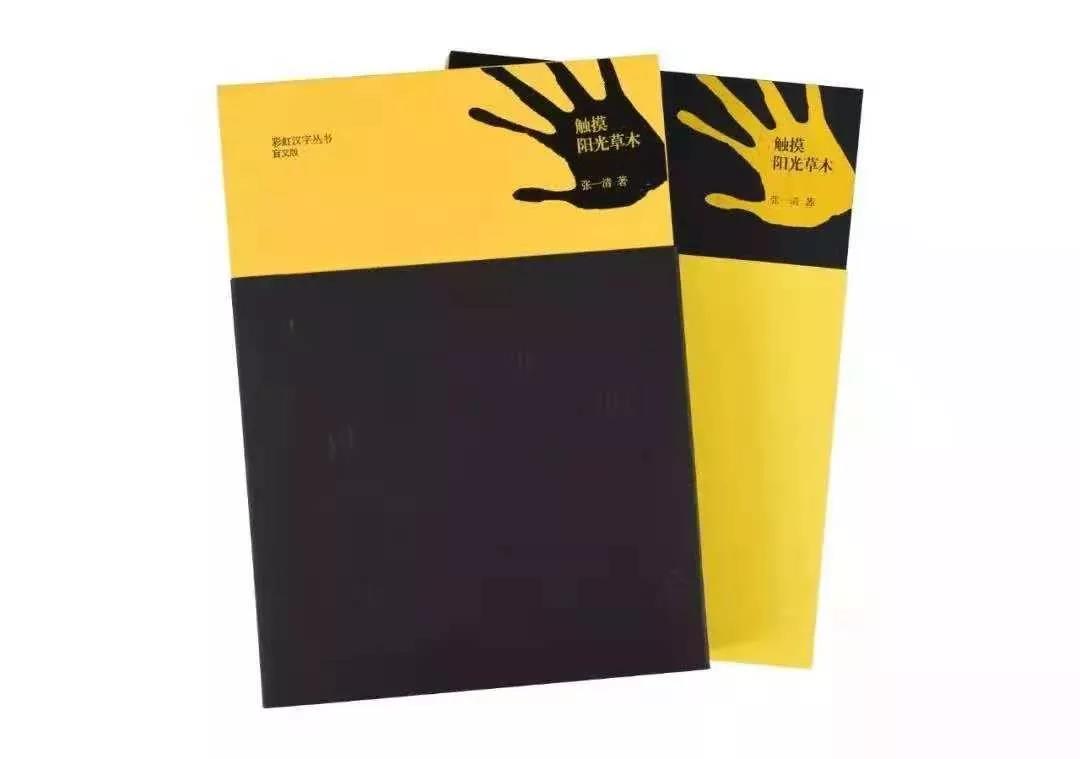
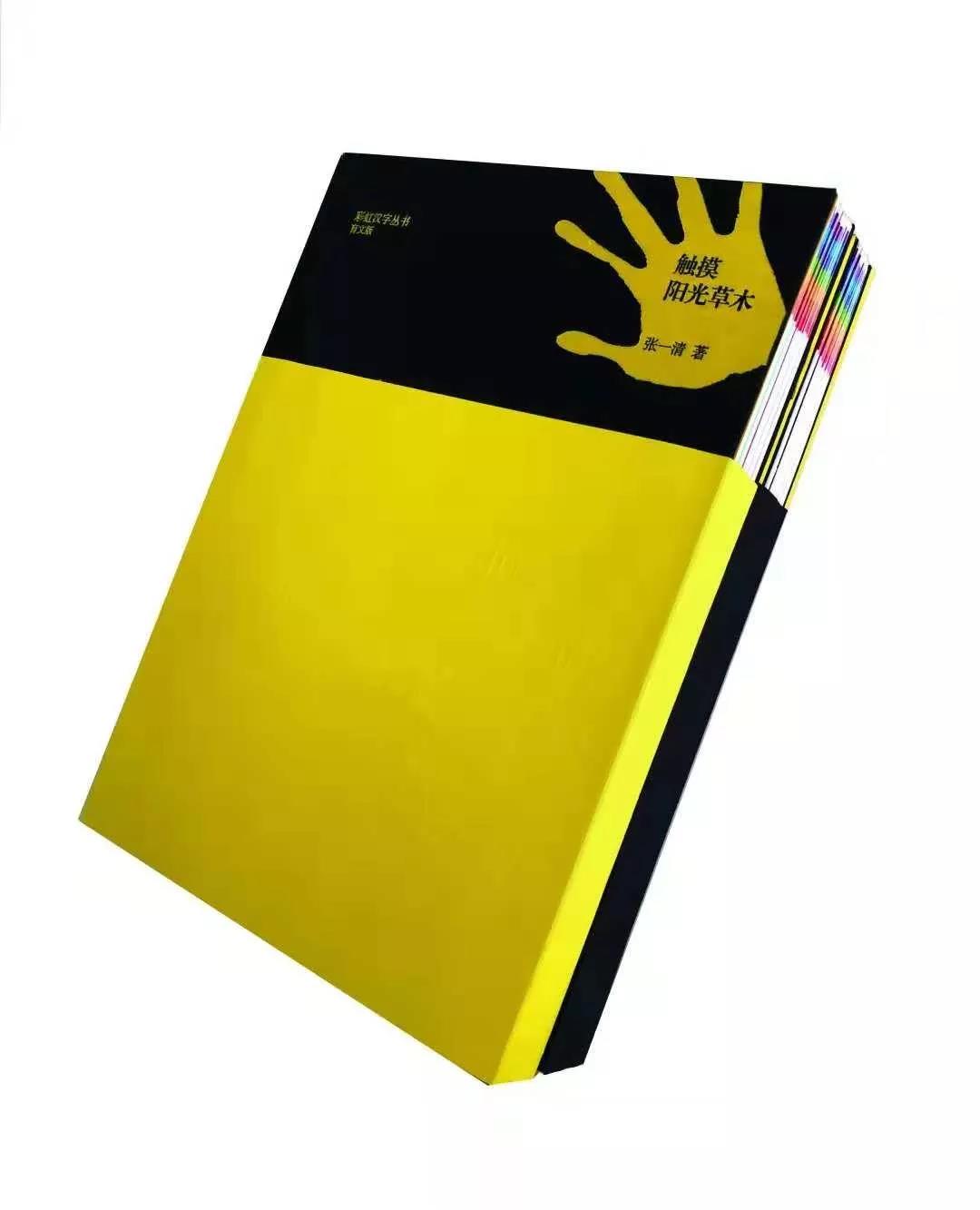
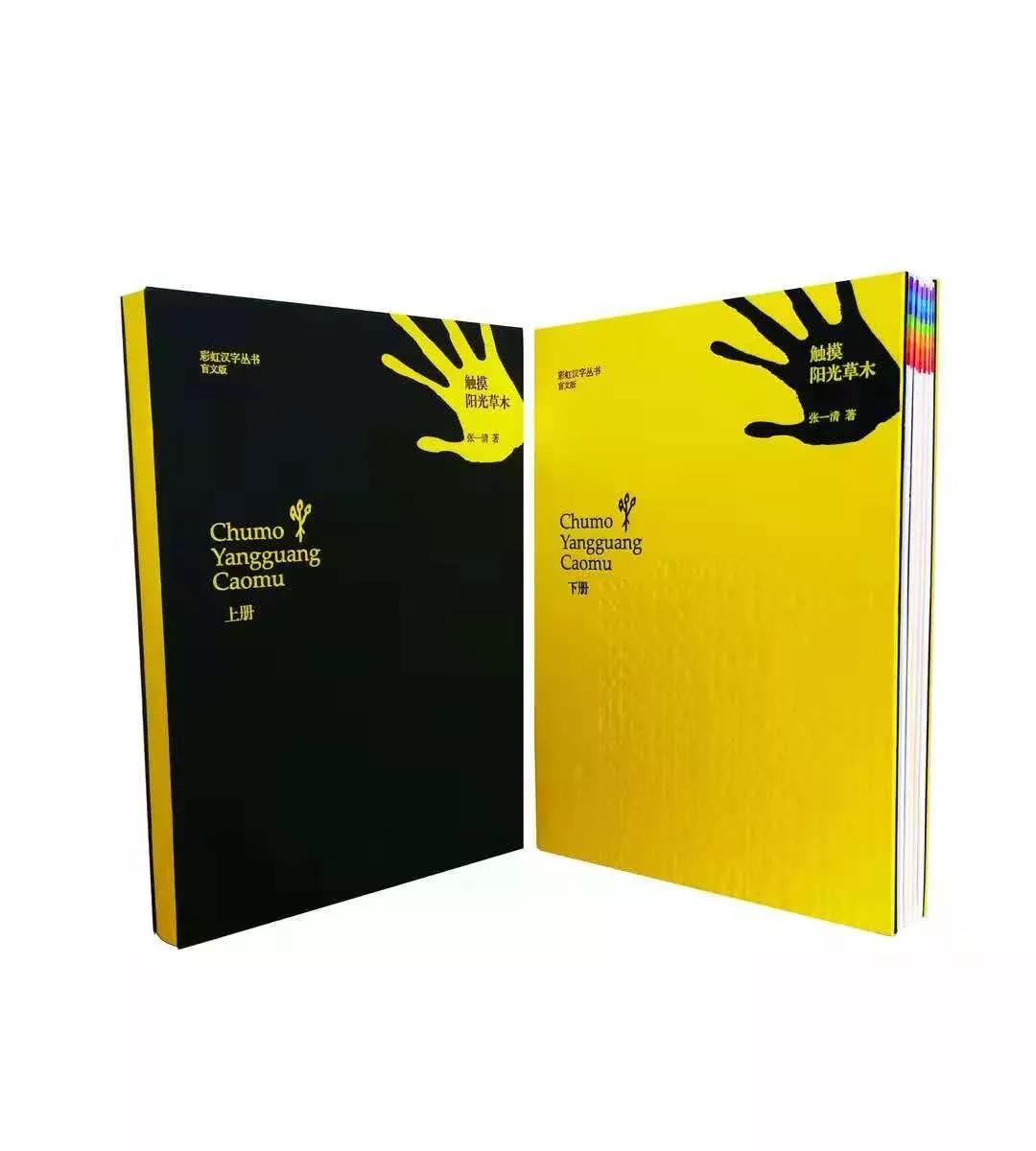
《彩虹汉字丛书(盲文版)·触摸阳光草木》自2017年11月出版以来,以其精美的设计、独特的编辑加工印刷技术、良好的触摸体验、传播传统文化的内容以及对特殊人群的人文关怀,先后获得2017“百道网”年度好书、“2017年度十大数字阅读作品”、“南京最美图书”等奖项,获得2018年度国家出版基金资助。
2018年11月5日晚八点,由阿里巴巴公益基金会主办的首届“中国自然好书奖”颁奖典礼上,该书又入选“年度十大自然好书”,图书责任编辑姜海涛获“年度编辑奖”。《彩虹汉字丛书·触摸阳光草木(盲文版)》这是国内难得一见的专门为盲人群体设计制作的书。
姜海涛在领奖中说,期望这套图书能够给盲人朋友架起一套领略汉字文化之美的彩虹,“大自然最常见的阳光、花草对盲生有自己的感受方式,他们看不到花开,却想触摸花开的声音。我们选取适合盲生理解,又与生活息息相关的汉字解读大自然,使盲点和图形在正文中做到完美结合,克服了以往的盲人图书触感不足和寿命过短的问题,最终实现可触摸、可听、可看,帮助全盲、弱视力和明眼读者共读一本书。”
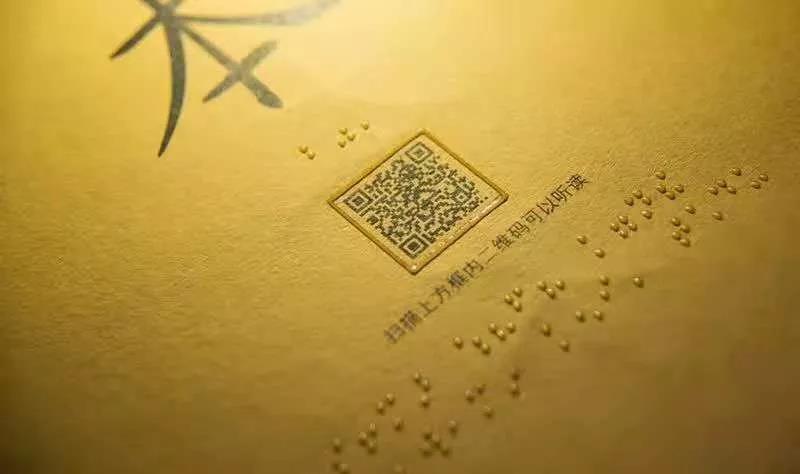
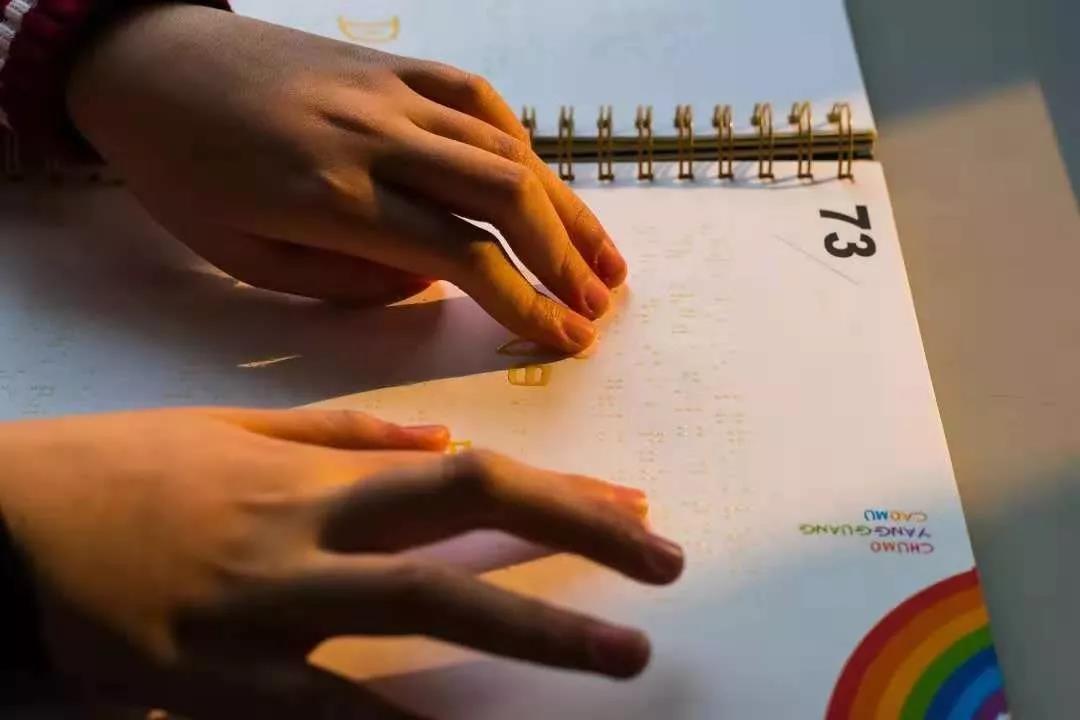
创新创业导师姜海涛从事图书出版行业20余年,她作为项目负责人,贯穿了《彩虹汉字丛书(盲文版)触摸阳光草木》的策划、编辑、设计的整个过程。以上的各项荣誉,是对这套图书从内容到设计再到数字技术融合运用的综合肯定。这也使她坚定信心,继续为盲童学习传统文化、体验汉字文化提供更加优质的精神文化产品。